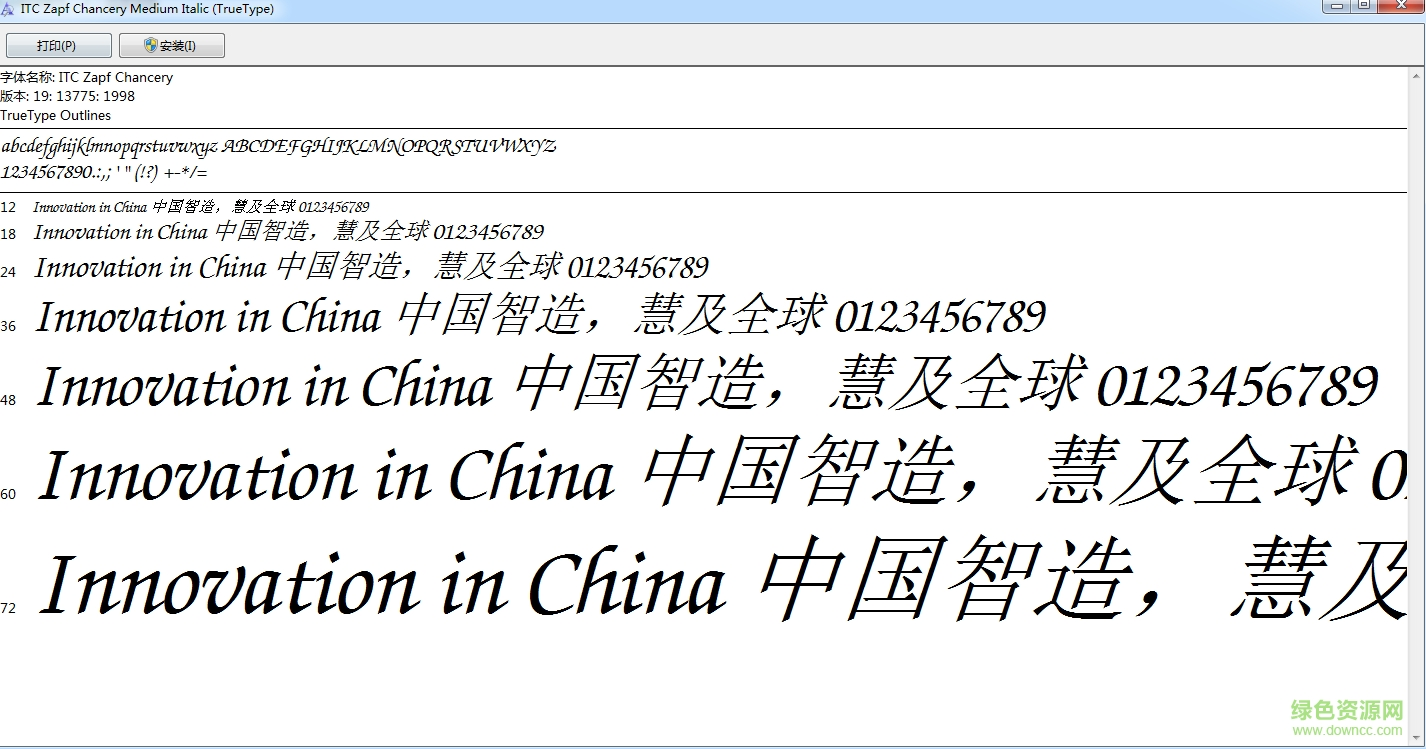
itc zapf chancery-常規(guī)斜體
itc zapf chancery字體是一款英文常規(guī)斜體字體,該字體風(fēng)格獨(dú)特,線條柔軟流暢,本站為你免費(fèi)提供itc zapf chancery的常規(guī)斜體字體下載地址!
斜體字體介紹
斜體是在正常字體樣式基礎(chǔ)上,通過(guò)傾斜字體實(shí)現(xiàn)的一種字體樣式。 中文(漢字)的斜體實(shí)際上都是單純將字面從正方形改為平行四邊形的“偽斜體”。斜體的大寫(xiě)字母不是手寫(xiě)體的字形,和偽斜體的字形幾乎一樣。而小寫(xiě)字母的筆畫(huà)多數(shù)是不一致的,主要是因?yàn)槠涫÷砸r線,適合連筆運(yùn)筆的緣故。
itc zapf chancery-常規(guī)斜體
斜體使用場(chǎng)合
1.表示強(qiáng)調(diào),喚起注意
2.書(shū)籍名稱、文章標(biāo)題、船舶名稱等
3.表示引用
4.外語(yǔ),如英文文章中夾雜的法語(yǔ)